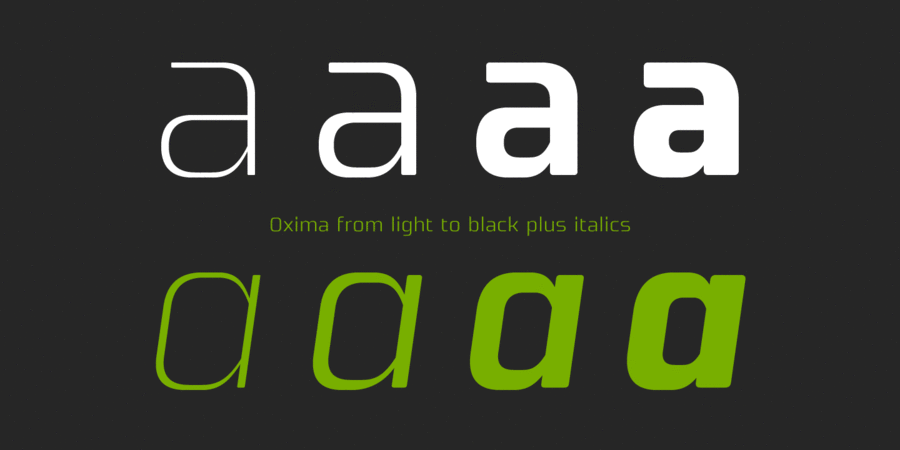
Це технічний гротеск із заокругленими кутами, який забезпечує поєднання суворої естетики з м'якими дрібними деталями. Його сильні індустріальні, але розбірливі форми роблять його ідеальним для сучасних і футуристичних проєктів. Шрифт підходить для використання в будь-яких розмірах, від заголовків до основного тексту та усього, що між ними. Oxima складається з 8 накреслень, кожне з них містить капітель та символи для багатьох мов на латинці та кирилиці. Шрифт розробив Пабло Балселлс у 2021 році.
Асоціації з сімейством шрифтів OximaОсобистість і характер гарнітури:
рівний, точний, логічний, автоматичний, техногенний, твердий, статичний, чіткий, стійкий, стабільний, тонкий, легкий, міський, сучасний, машинний, інженерний, урбаністичний, креслярський, скляний, крихкий, футуристичний, прозорий, спокійний, дротяний, худий, гладенький, гнучкий, чистий, модний, лаконічний, неоновий, надійний, впевнений, сталевий, байдужий, розумний, переконливий, серйозний, сильний, індустріальний, залізний, промисловий, залізничний, сексуальний, рішучий, спортивний, енергійний, комп'ютерний, крутий, амбітний, кінематографічний, сміливий